2023 年 21 種最佳傳單字體(免費和高級)
已發表: 2023-09-14您是一名平面設計師,正在尋找完美的字體來提升您的傳單設計嗎? 別再猶豫了! 在這篇博文中,我們將探索 21 種最佳傳單字體,它們一定會增強您的項目並吸引您的受眾。
我們將一起深入字體設計的世界,發現在審美吸引力和功能之間達到完美平衡的字體。 因此,讓我們開始尋找可以將您的傳單設計提升到新水平的字體!
在設計傳單時,選擇正確的字體至關重要。 它為您的信息定下基調,並可以決定或破壞您設計的整體影響。 有如此多的字體可供選擇,找到完美的字體可能會讓人不知所措。
這就是本文的用武之地! 我們進行了研究並編制了 21 種最佳傳單字體列表,保證讓您的設計脫穎而出。 無論您想要時尚現代的外觀還是俏皮異想天開的氛圍,我們都能滿足您的需求。
現在,讓我們深入研究印刷的世界,發現書面文字的力量。 版式不僅是選擇具有視覺吸引力的字體,更是選擇。 這是關於理解不同字體背後的心理以及它們如何影響觀看者的感知。
在本文中,我們不僅將探索最好的傳單字體,還將深入了解它們為什麼能夠如此有效地吸引受眾。 準備好釋放版式的潛力,將您的傳單設計提升到新的高度!
最佳高級傳單字體
希望將您的傳單設計提升到一個新的水平? 我們精心挑選的最佳優質傳單字體就是您的最佳選擇。 這些字體將為您的項目增添一絲專業和優雅,使它們脫穎而出。
少年
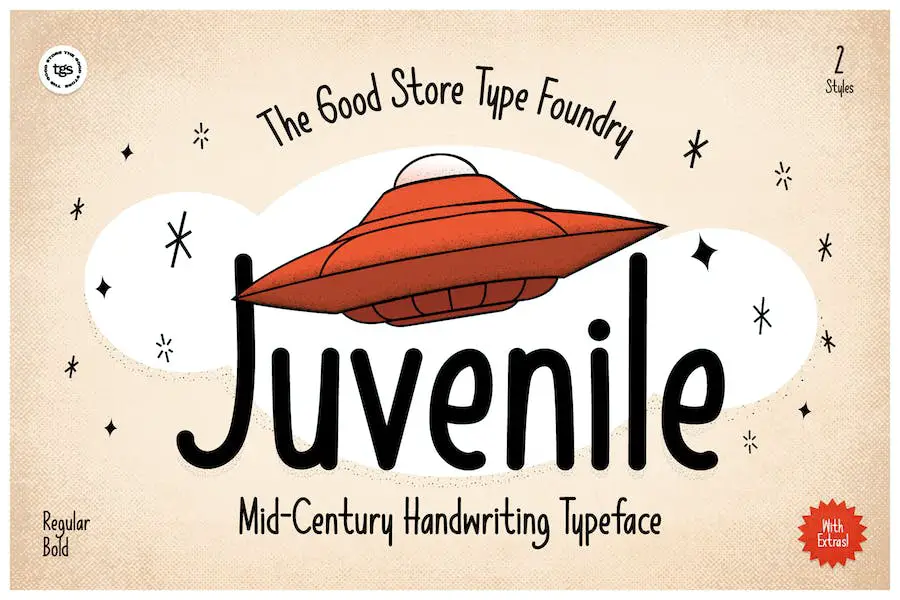
Juvenile 是一款迷人的手寫顯示字體,其靈感來自 20 世紀 50 年代異想天開的書法。 這種獨特的字體散發著青春的魅力,為任何設計項目增添了俏皮的氣息。
憑藉其真實和懷舊的感覺,Juvenile 非常適合製作引人注目的傳單,肯定會吸引觀眾的注意力。
Juvenile 以其獨特的風格為您的項目帶來令人愉悅的懷舊感。 其手工製作的外觀和不完美的字體捕捉了年輕手寫的精髓,使其成為旨在喚起純真和驚奇感的設計的理想選擇。
無論您是為兒童生日派對還是複古主題活動設計傳單,Juvenile 都能將復古魅力與現代魅力完美融合。
Juvenile 的突出特點之一是它的多功能性。 它提供了一系列的重量和款式,讓您可以嘗試並找到最適合您的設計需求的產品。 無論您喜歡大膽而有影響力的外觀,還是更精緻、異想天開的感覺,Juvenile 都能滿足您的需求。
其多種多樣的選項確保您可以創建與您所需的審美完美契合的傳單。
拉里薩
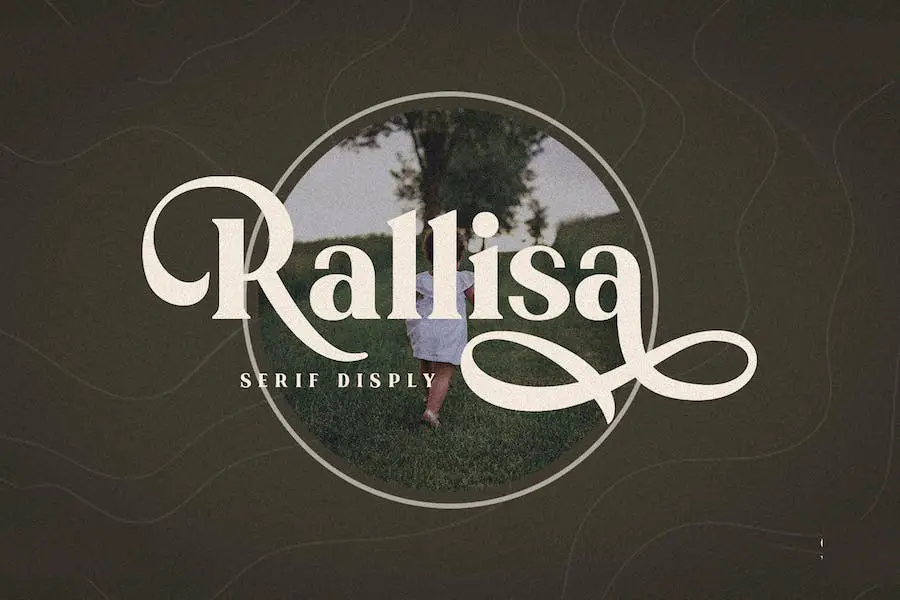
Rallisa 是一種時尚的襯線字體,非常適合為您的設計增添一絲優雅。 無論您是要創建食物菜單、海報、傳單還是印刷品,這種字體都會讓您的項目看起來令人驚嘆。 通過 Rallisa,您可以釋放您的創造力並探索它提供的無限可能性。
該字體專為增強項目的視覺吸引力而設計。 其時尚精緻的風格為任何設計增添了專業感。
無論您是在製作餐廳菜單、宣傳活動還是為企業製作傳單,Rallisa 都將提升整體外觀和感覺。
Rallisa 的突出特點之一是它的多功能性。 它可以與各種設計元素無縫協作,從而輕鬆集成到您現有的項目中。
無論您將其與大膽的圖像、鮮豔的色彩還是簡約的佈局搭配,Rallisa 都能輕鬆補充和增強整體設計美感。
高高在上
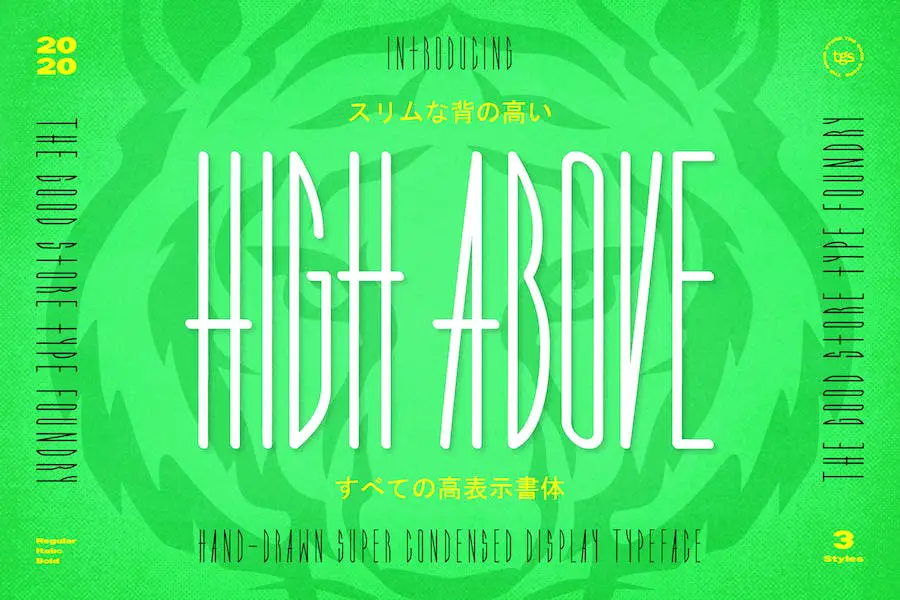
High Below 是一款超濃縮的顯示字體,為希望增強傳單設計的圖形設計師提供了獨特的手繪風格。
該字體具有三種樣式可供選擇——常規、粗體和斜體——非常適合為任何項目增添創意和個性。
這種非常酷的傳單字體旨在使您的文字脫穎而出並吸引註意力。 其簡潔的風格使您可以在有限的空間中容納更多信息,而不會犧牲可讀性。
無論您是在製作促銷傳單、活動邀請函,甚至是專輯封面,High Below 都會為您的設計帶來專業且引人注目的外觀。
High Upper 的常規風格非常適合創造時尚和現代的設計。 其簡潔的線條和平衡的比例使其用途廣泛且易於使用。 如果您想在傳單中添加大膽的宣言,High Below 的大膽風格就可以做到這一點。
溫迪圖姆
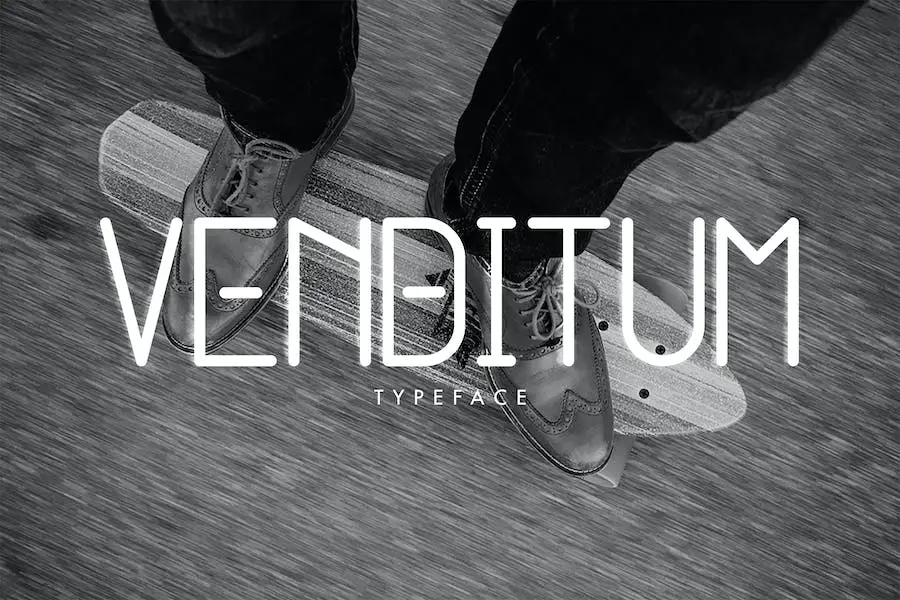
Venditum 是一款現代單線字體,融合了現代設計元素、未來美學和 Tumblr 風格的風格。 這種字體以其多功能性和時尚的外觀而聞名。
借助 Venditum,圖形設計師可以使用增添現代感和時尚感的字體來增強他們的項目。 familia 字體將現代性與簡潔性完美融合,使其適合各種設計。
Venditum 的單線設計賦予其乾淨、時尚的外觀,非常適合用於傳單和其他宣傳材料。 其現代美學為任何設計增添了一絲精緻感,使其在人群中脫穎而出。
Venditum 融合了 Tumblr 風格的元素,為您的項目帶來獨特而時尚的氛圍。 無論您是為音樂活動設計傳單還是為時尚品牌設計宣傳海報,這種字體一定會吸引觀眾的注意力。
邊緣
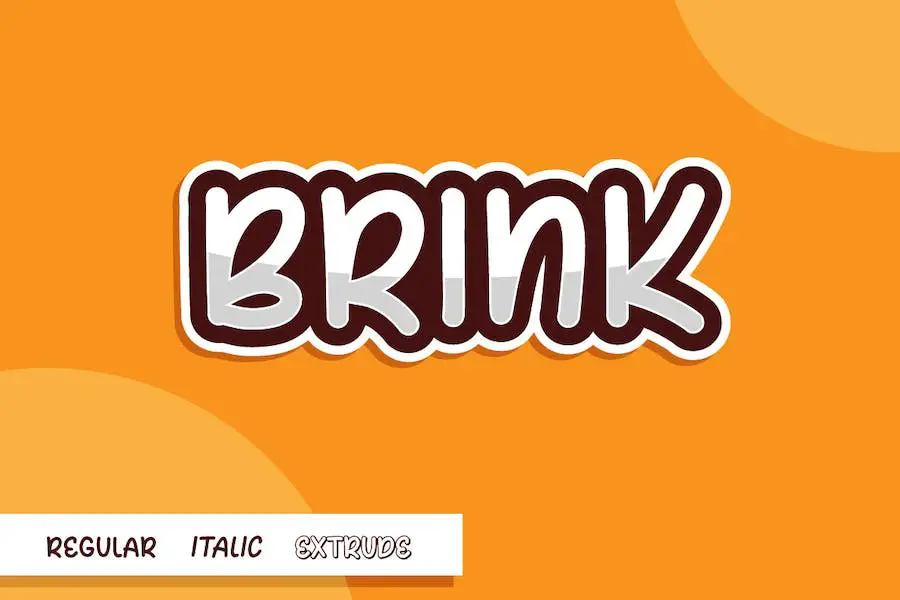
Brink 是一種有趣又俏皮的漫畫字體,非常適合為任何創意項目增添一絲奇思妙想。
無論您是設計故事書、漫畫書、學校項目、傳單、書名、廣告,甚至是社交媒體內容或徽標,Brink 都是一款多功能字體,可以讓您的設計栩栩如生。
憑藉其簡單而誘人的設計,Brink 抓住了經典漫畫字體的精髓。 其俏皮的曲線和獨特的字符形狀使其脫穎而出,並為任何文本增添一抹個性。
無論您想創建大膽的標題還是為您的設計添加古怪的風格,Brink 都能滿足您的需求。
Brink 的一大優點是它易於閱讀。 雖然它具有俏皮和漫畫風格的外觀,但字母仍然清晰易讀,確保您的信息有效傳達。
當將字體用於傳單、廣告管理或任何其他以可讀性為關鍵的媒體時,這一點尤其重要。
傳單
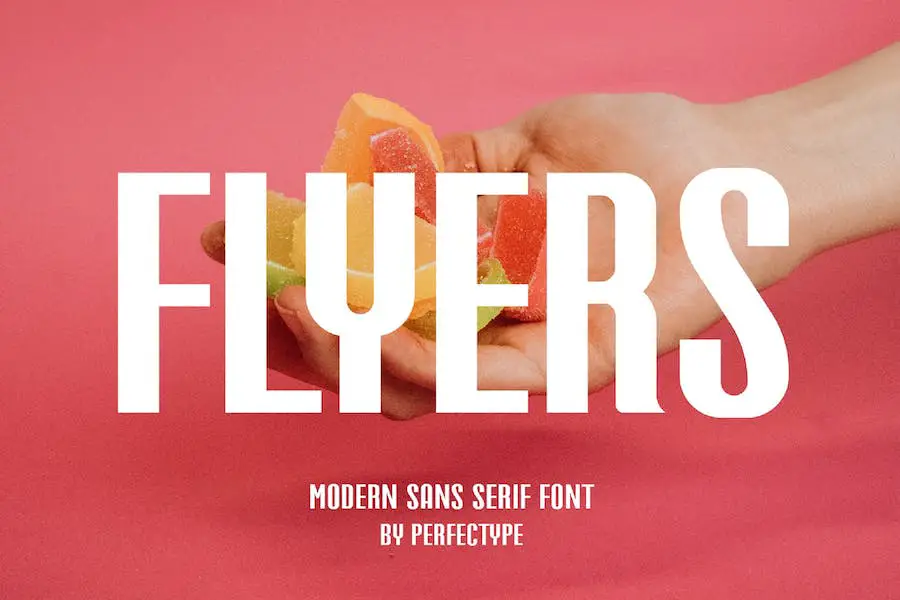
Flyers 是一種從極簡主義徽標中汲取靈感的字體,使其成為希望增強項目設計的圖形設計師的完美選擇。 憑藉其時尚簡潔的美感,該字體非常適合創建引人注目的小冊子、模板、視頻和廣告品牌。
無論您是在設計徽標還是設計優雅的邀請函,Flyers 都會為您的視覺創作增添一絲精緻和美麗。
這種多功能字體不僅適合專業用途,而且也非常適合個人項目。 無論您是在進行佈局設計還是開始優雅的 DIY 項目,Flyers 都將提升您的創作並賦予它們精美的外觀。
它的靈活性使您可以在各種設計項目中使用它,讓您可以自由地探索不同的風格和想法。
蘭博斯
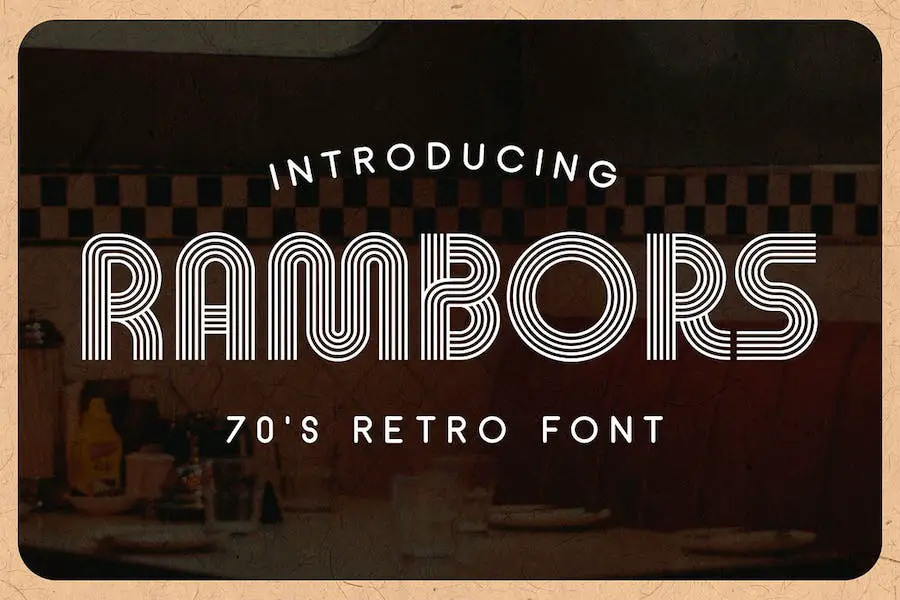
Rambors 是一款多行顯示字體,從 70 年代的設計中汲取靈感。 這種字體具有未來感和有趣的圖形風格,非常適合為您的項目添加獨特且引人注目的元素。
其多行功能可實現富有創意且視覺上有趣的文本設計。
Rambors 的突出特點之一是它能夠喚起懷舊感,同時仍保持現代和新鮮的外觀。 該字體將 70 年代的複古美學與現代風格完美融合,使其適用於各種設計項目。
憑藉其多行設計,Rambors 為創建迷人的文本組合提供了無限的可能性。 字體內的線條增強了整體視覺衝擊力,使其成為海報、傳單和其他宣傳材料的理想選擇。
巴斯馬拉
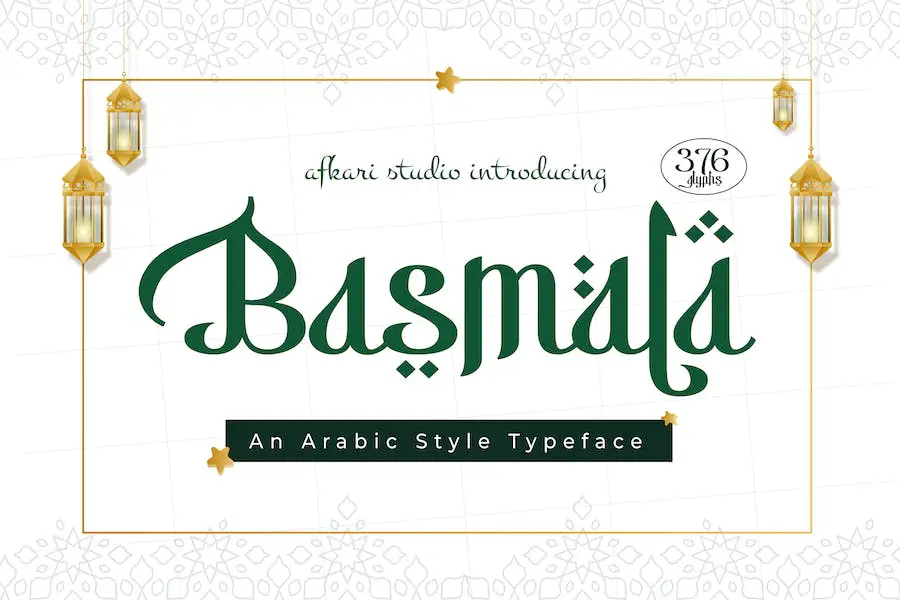
Basmala 是一種新的阿拉伯風格字體,可為您的設計帶來優雅和伊斯蘭風格。 作為一種阿拉伯風格的顯示字體,它是專門為那些想要將伊斯蘭風格融入到他們的項目中的平面設計師設計的,特別是在齋月期間。
Basmala 憑藉其獨特而華麗的字體,為任何設計增添了獨特的阿拉伯美學。
這種字體非常適合創建需要傳達伊斯蘭主題的迷人傳單和宣傳材料。 其複雜的設計和對細節的關注使其脫穎而出並吸引觀眾的注意力。
無論您是設計齋月活動傳單、伊斯蘭藝術展覽的海報,還是中東餐廳的菜單,Basmala 都可以提升您設計的整體外觀和感覺。
Basmala 的關鍵屬性之一是它的多功能性。 該字體可用於裝飾和信息目的,具體取決於您的設計需求。 您可以使用它來創建引人注目的標題、標頭和號召性用語短語,立即吸引觀眾的注意力。
此外,優雅流暢的字體使 Basmala 易於閱讀,確保有效傳達您的信息。
十二海洋
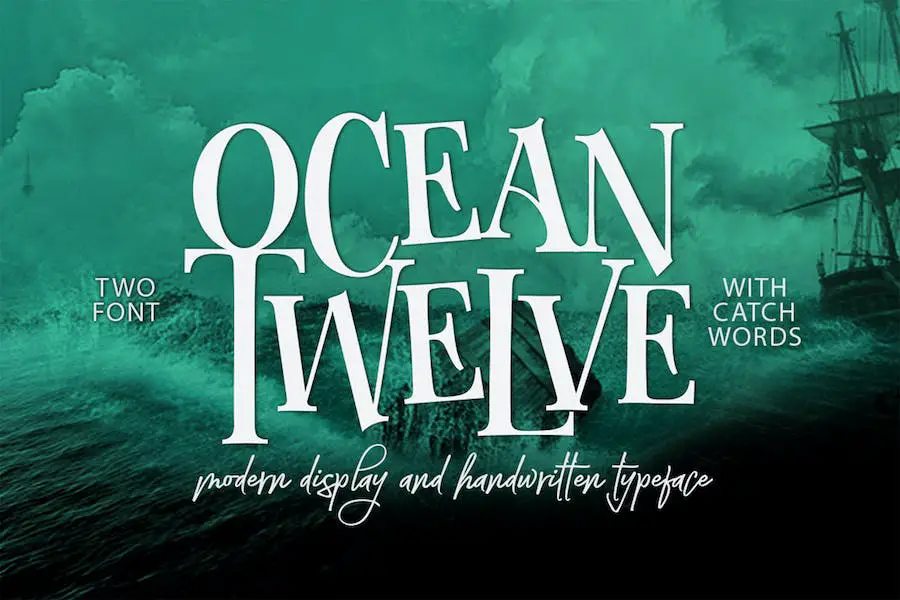
Ocean 12 是一種現代顯示和手寫字體,其靈感來自於海報、書籍封面和 CD 封面上常見的複古字體。
憑藉其獨特而時尚的設計,該字體非常適合希望增強項目視覺吸引力的圖形設計師。 它為任何設計增添了一絲懷舊和優雅,使其在人群中脫穎而出。
十二海洋字體融合了簡潔的線條和手繪元素,賦予其獨特的藝術外觀。 其多功能性使其可用於各種設計目的,包括傳單、小冊子、徽標等。
無論您是要創建復古風格的海報還是時尚的專輯封面,這種字體都能滿足您的需求。
十二海洋字體的突出特點之一是它對細節的關注。 每個角色都經過精心製作,展現出複雜的筆觸和曲線,給人一種手工製作的感覺。
這種工藝水平為您的設計增添了個人風格,使它們對您的受眾來說更具吸引力和難忘。
乏力
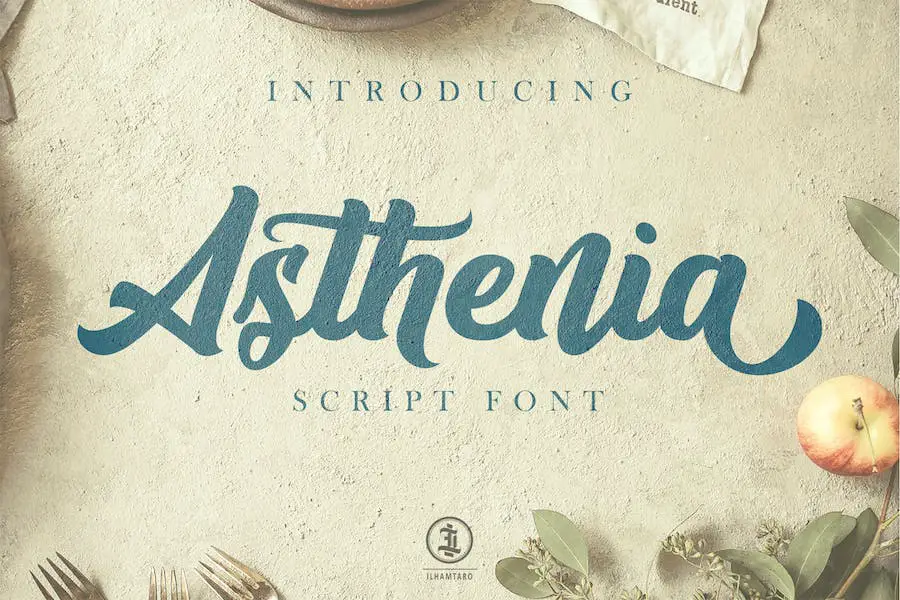
Asthenia 是一種創意設計的腳本字體,提供多種選項來增強您的項目。 該字體具有超過 420 個字形,包括大寫、小寫、數字、標點符號、連字和替代字符,可以輕鬆進行自定義。
無論您是設計標識、海報、傳單、T 卹設計、包裝、品牌還是商品,Asthenia 都能滿足您的多功能需求。
該字體廣泛的字符集提供了無限的定制可能性,使其非常適合任何需要優雅和創造力的項目。
從時尚現代的標識到引人注目的海報和傳單,Asthenia 的替代字符和連字可讓您為您的設計增添獨特的風格。 憑藉其一系列的數字和標點符號,您還可以確保整個工作的一致性和連貫性。
切西西斯
Cecision 是一種現代時尚的襯線字體,可為任何設計項目增添一絲優雅。 憑藉其多功能性,它可用於各種製作創意,例如卡片、品牌、標籤等。
當您將 Cecision 融入您的創作中時,您會對它產生的令人驚嘆的結果感到驚訝。 其時尚和現代的風格將把您的設計提升到一個全新的水平。
無論您是製作傳單的平面設計師還是製作宣傳材料的企業主,Cecision 一定會給您留下深刻的印象。 使用這款精美的字體為您的項目帶來精緻和專業的外觀。
羅克斯維爾
ROXVEIL 是一款出色的顯示字體,專為各種圖形設計項目而設計。 其多功能性使其非常適合用於標題、大文本、品牌、標識以及海報、傳單和廣告等各種宣傳材料。
ROXVEIL 憑藉其獨特而引人注目的設計,為任何設計項目增添了一抹優雅和精緻。
這種引人注目的顯示字體非常適合創建有影響力的標題,立即吸引觀眾的注意力。 其大膽而獨特的字體確保您的信息脫穎而出,給人留下持久的印象。
無論您是設計雜誌封面還是促銷傳單,ROXVEIL 迷人的外觀都會讓您的文字更加流行。
在品牌和標誌設計方面,ROXVEIL 提供了無限的可能性。 其時尚和現代的美學讓您能夠創建一個真正代表您品牌個性的標誌。
有了 ROXVEIL,您的品牌將散發出專業精神和獨特性,讓您在競爭中脫穎而出。
鹽星
Saltstar 是一種時尚而精緻的無襯線字體,散發著現代感和優雅感。 這款字體的設計注重細節,具有圓角和獨特的形狀,可立即提升您的項目設計。
憑藉其附加的連字和替代字符,Saltstar 為創意表達提供了無限的可能性。 無論您是為商務活動設計傳單還是為產品發布會設計促銷海報,這種字體一定會給人留下深刻的印象。
對於有趣好玩的傳單,您可以探索更具創意和裝飾性的字體。 確保您選擇的字體易於閱讀且清晰,無論是印刷還是數字格式。 嘗試不同的字體組合,以找到美觀和可讀性之間的完美平衡。
最終,相信您的直覺並選擇與傳單目的產生共鳴並符合您的設計願景的字體。
結論
回顧一下,在本文中,我們討論了圖形設計師可以用來增強其項目設計的 21 種最佳傳單字體。 這些字體是根據其審美吸引力和多功能性精心挑選的。
通過將這些字體合併到您的傳單中,您可以創建視覺上令人驚嘆且引人注目的設計,從而吸引您的受眾。